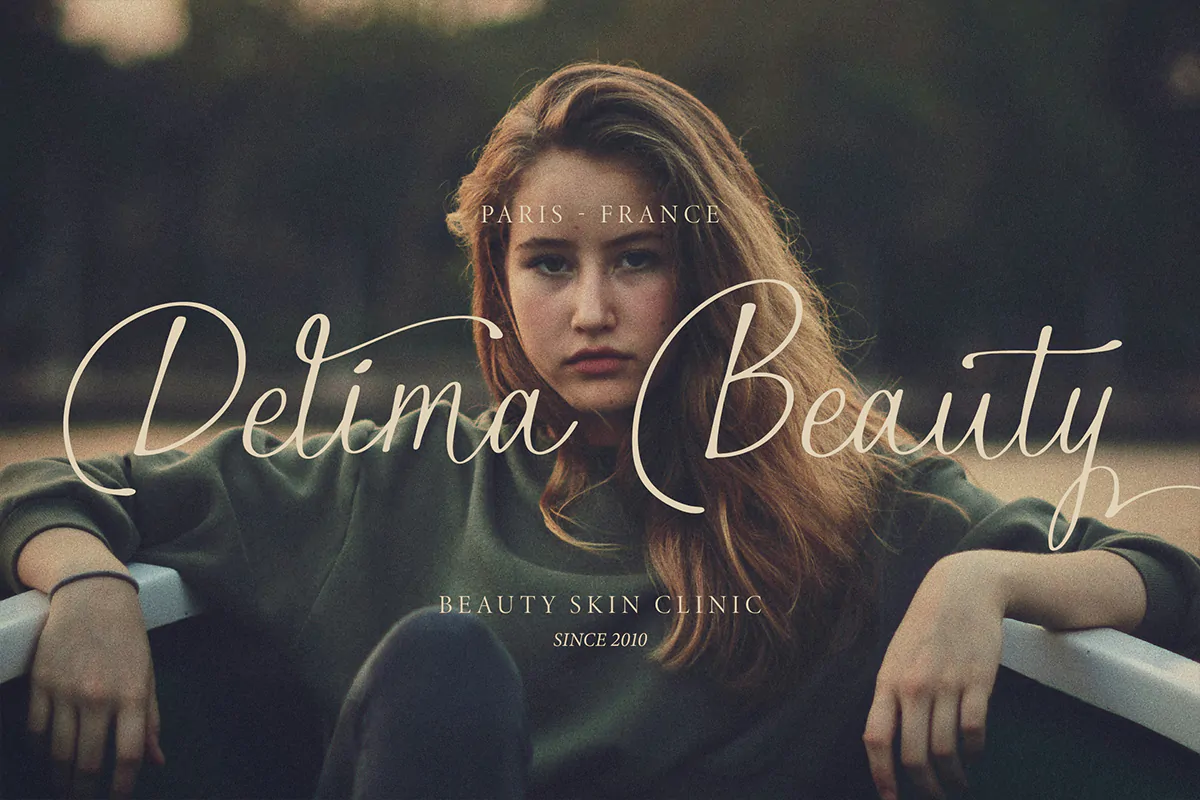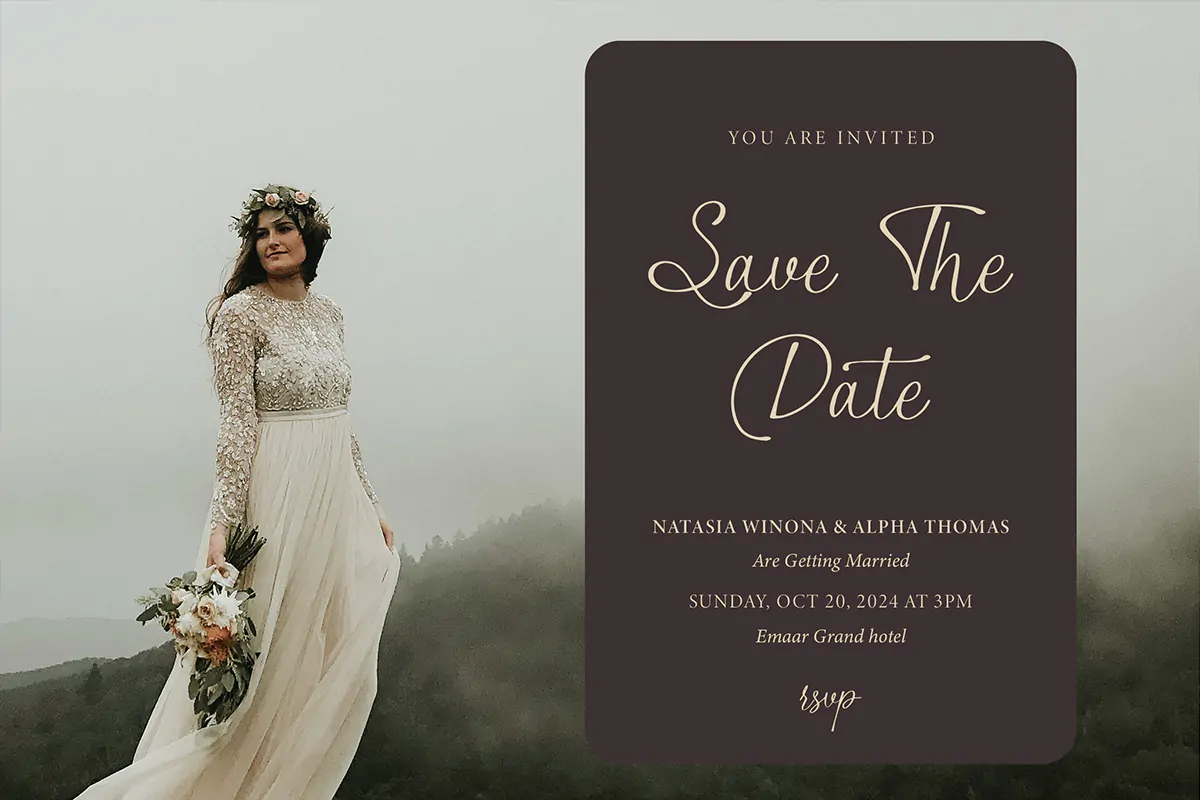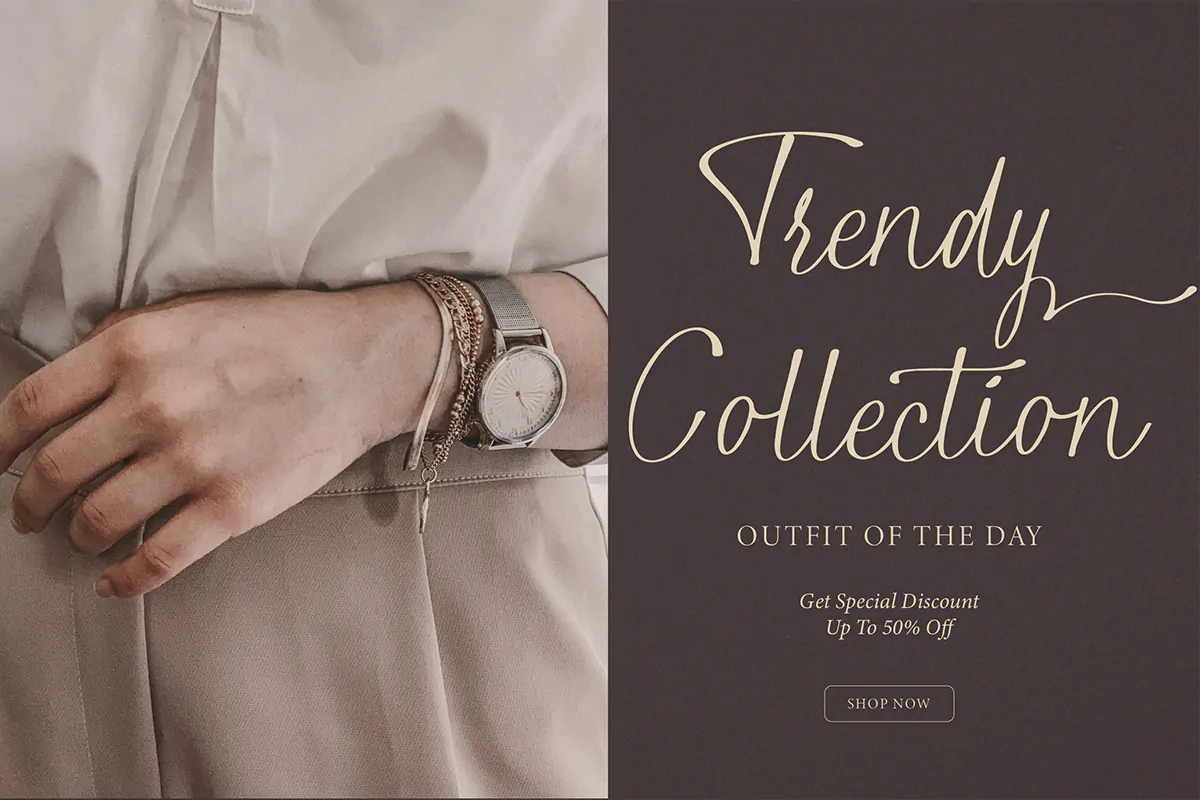
فونت دستنویس زیبای Alphiness
فونت دستنویس انگلیسی
فونت دستنویس زیبای Alphiness یک قلم انگلیسی است که با دو وزن معمولی و مورب طراحی شده است و مناسب برای استفاده در پروژههای گرافیکی مختلف همچون طراحی کارت عروسی، کارت تبریک، کارت ویزیت، بسته بندی محصولات، پوستر و … میباشد.